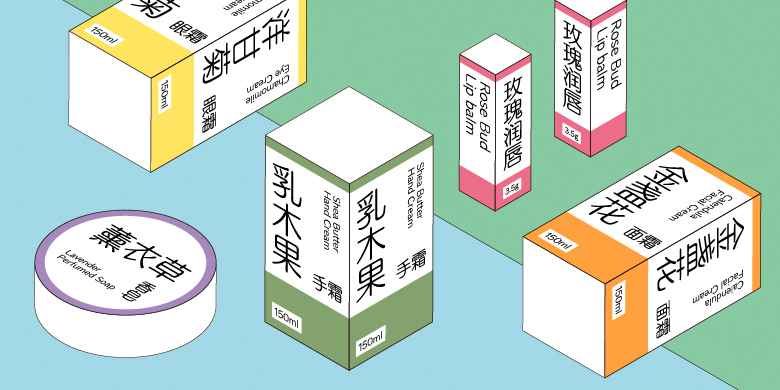
这款字在保有严肃印象的同时又加进了适度的时尚性,并以「圆体」方式展现出来,可以作为继圆体之后的「准圆体」使用,比圆体更能展现出成熟、柔和的形象。
まじめな印象を与えながらも適度なファッション性を加味した書体を“ラウンドタイプ”で表現した書体です。丸ゴシック体に続く、準定番書体としてご使用いただきたい書体です。丸ゴシック体よりも《大人で柔らかい》イメージを表現できます。
方正FW轻吟体家族